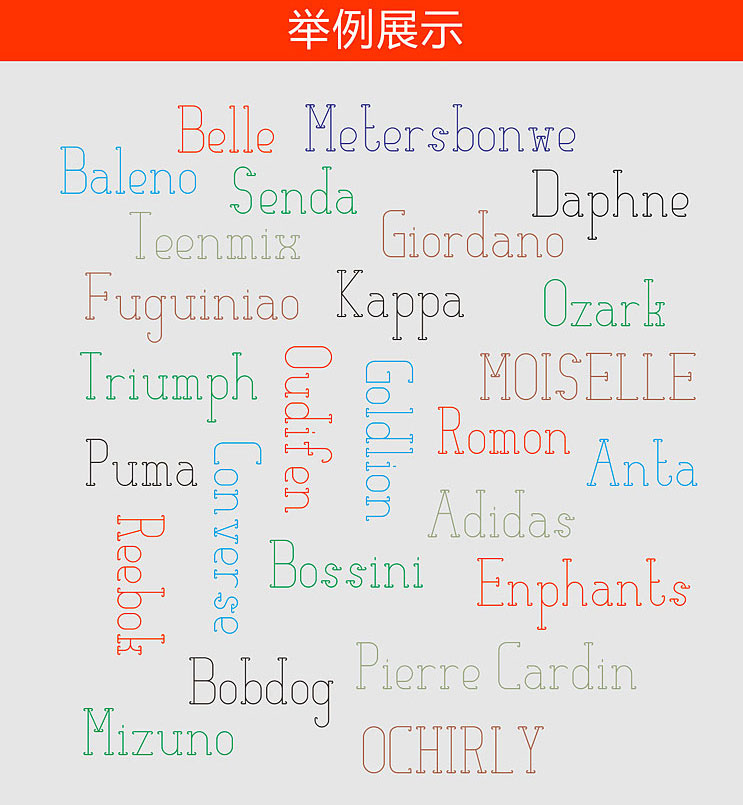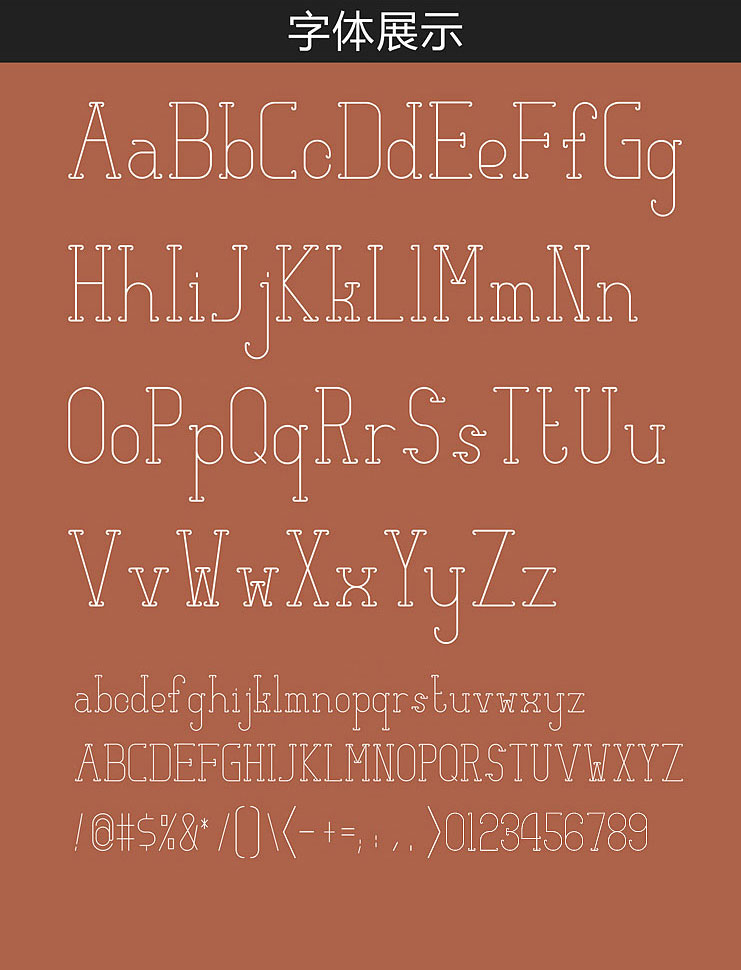
Jiye spiral是一款免費字體,是早在2013年的時候孫新恆先生做的,他已經都忘記了,前幾天我翻找文件時突然看到告訴他後,他才想起還有這麼一款字體。
Jiye spiral為孫新恆先生早期在研究字體字庫時設計的一款英文字庫產品,也許、可能、大概,該字體有些不足之處,但在某些場景中應用效果還是很不錯的。
Jiye spiral適合大字號顯示,因為字體的裝飾元素在極小字號時可能無法清晰顯示,也體現不出Jiye spiral的本色效果,所以,字體越大,越能體現它的美麗。
Jiye spiral是一款偏年輕、偏女性的字體產品,適合於店招、詳情頁面、寶貝描術、海報、廣告、英文標題、輔助裝飾圖案或元素及一些印刷品中。
下面是Jiye spiral的美麗容顏,它高挑纖細、婀娜多姿,絕代風華,哈!哈!哈!不能再吹了。